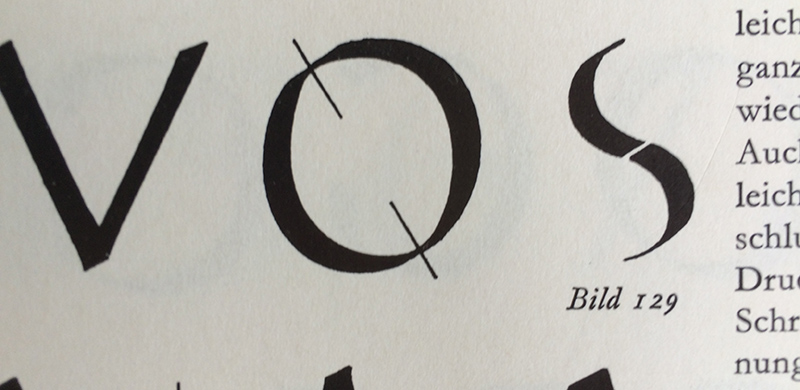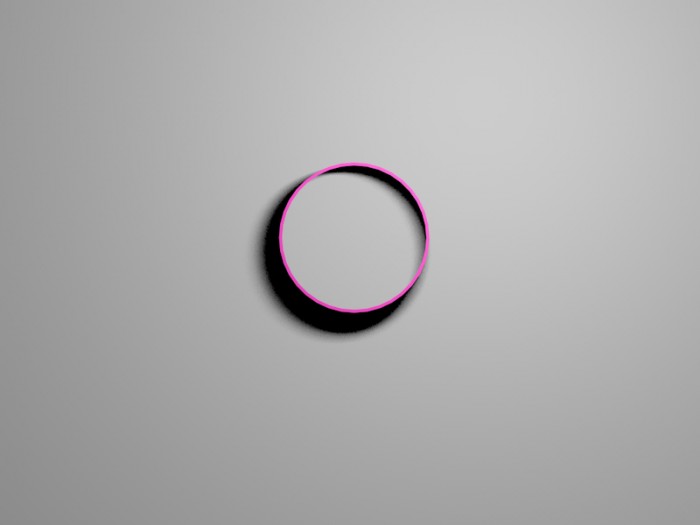
Wie erklärt man den Begriff »Schattenachse«?
Interessante Begriffshinterfragung jedenfalls – ich muss gestehen, daß ich bisher völlig theoriefrei und historisch unbeleckt die Schattenachse mit den ursprünglichen römischen Versalien, natürlich in Stein gemeisselt, in Verbindung gebracht habe. Da fällt ja auf jeden Fall ein Schatten, der die Buchstabenform auch noch entsprechend betont.
Ich hab noch eine anschauliche Definition gefunden, die den Begriff "Achse" schlüssig beinhaltet:
Die Schattenachse (Neigungsachse) ist jene Linie der Glyphe, die bei Rundungen die Stellen mit der geringsten Strichstärke verbindet .
Aber auch nicht sonderlich präzise. Schließlich sind die »leicht bananenförmigen« Striche der Glyphe selbst »Linien« (halt gekrümmte), die diese Stellen verbinden. Vielleicht eher
eine Gerade durch die zwei Punkte eines kurvenförmigen Glyphensegments mit der geringsten Strichstärke
oder so ähnlich …
Und wenn die sich durch unzweifelhafte Verwendung bewährt hat, braucht man auch nicht über einen womöglich »besseren« Begriff spekulieren.
Naja, aber dass ein Mensch wie Martin, der an sich selbst und andere hohe Maßstäbe in Sachen Sorgfalt und Akribie ansetzt, mit einem so unpräzise formulierten Fachbegriff nicht glücklich sein kann, das ist schon nachvollziehbar. Und die Welt würde keine schlechtere, wenn man statt des irreführenden Begriffes einen sinnvolleren etablieren würde. Das Ganze erinnert mich ein wenig an die Versal-Eszett-Diskussion: Warum mit einem schlechten Kompromiss leben, wenn es eine bessere Alternative gibt? Beim Versal-Eszett existiert sie bereits; bei der Schattenachse, so scheint mir, muss sie noch erfunden werden.
Was wäre denn eine inhaltlich treffende Bezeichnung für das Ding?  :-?
Die gibt es ja schon immer. Es bedarf keines neuen Begriffes.
Forssman, de Jong
Detailtypografie
Neigungsachse
Bei Schriften mit wechselnder Strichstärke schwillt der Strich um eine Achse herum an und nimmt wieder ab. Diese Achse kann gar nicht, wenig oder stark geneigt sein.
Mir ging es bei der Schattenachse darum, daß ich es genau wissen will. Das ist alles.
Ich schreibe an einem Buch für Leser ohne Vorkenntnisse und erkläre dort ständig etwas. Dabei mache ich mir Dinge klar, über die ich seit langer Zeit nicht nachgedacht habe. Und ich stoße auf Fragen, die neu sind. Und auf unklare Begriffe. Da mein Text für Laien geschrieben wird, erkläre ich Begriffe. Und dann stößt man mitten in allen möglichen Lektüren und Themen auf so ein merkwürdiges Wort, denkt kurz darüber nach und dann: Schattenachse, das kenne ich doch? Woher? Sonne, Mond und Sterne? Dann sucht man und findet auch. Die Definition dieser Schattenachse mußte ich mir erklären lassen: Achse vom Mittelpunkt des lichtwerfenden zum schattenwerfenden Körper in einem Kegel, der wegen der Rundung der Körper entsteht. So ungefähr.
In der Typografie gehört die Schattenachse nicht zu meinem aktiven Wortschatz, nur zum passiven. In meiner Ausbildung gab es das Wort nicht, in der Literatur kommt es nur selten vor. Die Trefferanzahl dieses Wortes bei Google in Bezug aus Typografie ist nicht groß. Nun haben wir gesehen, daß es wahrscheinlich erst nach 1990 aufkam. Das ist noch kein Zeitraum, für den man sagen kann: wir verwenden den Begriff schon lange, die ursprüngliche Bedeutung ist verschwunden, es ist eine Art unübersetzbares Fremdwort geworden und bezieht aus dem Gebrauch seine Legitimität. Kann man nicht sagen nach rund 20 Jahren. Könnte man auch nicht nach 40. Dieser Begriff hat eine Geschichte. Aber offenbar liegt die im Dunkeln. Der Begriff wird, so wie ich jetzt den Eindruck gewonnen habe, verwendet, ohne daß jemand sich über seine Bedeutung erkennbar Gedanken macht. Man spekuliert so vor sich hin, und das kann man ja auch gut. Schatten in den gemeißelten Inschriften. Na, aber der wandert ja mit der Sonne, und wenn die links oben steht über den Trajan-Buchstaben, dann liegen die Schatten in den Haarlinien. Das kann es nicht sein. Schatten der Feder. Aber wie kommt man denn auf so etwas? Warum denkt man: Ich nenne die gebogenen Striche Schatten? Das denkt niemand, das ist eine nachträgliche Erklärung für einen vielleicht versehentlich entstandenen Begriff. Einleuchtender erscheint mir, daß der alte Begriff der Schattenstriche da hineinkam, Schattenstrich als Wort für den dunklen Strich. Zu diesen läuft die Achse aber nicht parallel, denn sie sind gebogen, nichts kann zu ihnen parallel laufen. Mir erscheint dieser Begriff undeutlich, und seine Herkunft ist hier nicht ermittelt worden. Eine andere Frage dazu: Gibt es diesen Begriff in anderen Sprachen, aus denen er durch Übersetzung zu uns gekommen sein könnte? Gibt es diese Achse überhaupt in anderen Sprachen? Im Englischen finde ich sie beschrieben als Verbindung der dünnsten Punkte. Einfacher und eindeutiger geht es nicht. Ohne geheimnisvoll dunkle Schatten. Wie sieht das im Französischen aus und im Italienischen?
Es gibt auch andere Begrifflichkeiten, die ohne eine Achse auskommen, die das Bild vom Schreiben definieren, nicht von der nachträglich analysierenden Geometrie durch Anlegen des Lineals, wie etwa die »Schwellung« und die »Druckverstärkung«. Letzteres verstehe ich noch nicht. Wenn ich das Schriftschreiben nach Frutigers Schilderungen richtig verstanden habe, wird der Druck am Anfang und am Ende der Schwellung verstärkt, um sie lebhafter aussehen zu lassen. Man muß den Druck nicht verstärken, damit die Linie breiter wird, das ist nur bei der Spitzfeder so. Und mit der kann man keine klassizistische Schrift schreiben, die muß man ja zeichnen. Also die Druckverstärkung habe ich auch noch nicht kapiert. Ist mir zur Zeit auch nicht dringend, das kann ich sicherlich noch irgendwo ermitteln. Gerard Unger spricht von den Positionen der Bogenmaxima. Das ist ungewohnt abstrakt für meinen Geschmack, aber es ist auch sehr exakt. Und es ist ein Begriff aus dem Schreiben, nicht aus dem Nachmessen.
Die Begriffe beeinflussen das Denken über Schrift. Nach all diesen Überlegungen frage ich mich, ob das Sprechen über eine Achse dem Betrachter die Schrift vom Leibe hält, eben weil es ein geometrischer Begriff ist, für den sich der Schriftschreiber nie interessiert hat. Spricht man über die Schwellungen, die Verstärkungen oder auch die Bogenmaxima, dann spricht man aus der Perspektive des Zeichners und sieht dadurch die Schrift auch anders. Man denkt mit dem Schreibwerkzeug, nicht mit dem Lineal.
Zum Schluß: Die Genauigkeit ist dem Beruf des Typografen eingeschrieben. Wenn wir Buchstabenabstände mit (digitalem) Seidenpapier ausgleichen, sollten wir uns in unseren Begriffen ebenso um Genauigkeit bemühen.
Naja, aber dass ein Mensch wie Martin, der an sich selbst und andere hohe Maßstäbe in Sachen Sorgfalt und Akribie ansetzt, mit einem so unpräzise formulierten Fachbegriff nicht glücklich sein kann, das ist schon nachvollziehbar.
Er ist aber nicht unpräzise formuliert. Wenn Begriffe unpräzise verwendet werden, bin ich ja selbst der erste, der sofort einen Artikel schreibt und versucht, der unpräzisen Verwendung entgegegenzuwirken. Das sind aber zwei verschiedene Paar Schuhe.
Hm, mir erscheint Neigungsachse deutlich präziser und verständlicher zu sein als Schattenachse. Ich sollte mir wohl dringend Martins Buch kaufen, wenn es fertig ist.  ;-)
Ich würde also mal schauen, welche Standardwerke der Kalligrafie vor Frau Korgers Buch kamen. Vielleicht findet sich ja da mehr zur Schattenachse.
Google meint, dass es in "Ursache & Wirkung" von Erik Spiekermann, 1982, vorkäme. Ich habe allerdings die Stelle nicht gefunden …
Wobei das Licht nicht punktförmig strahlen darf, sonst käme das einer Drehung der Feder beim schreiben gleich und die Achse wäre somit eine andere.